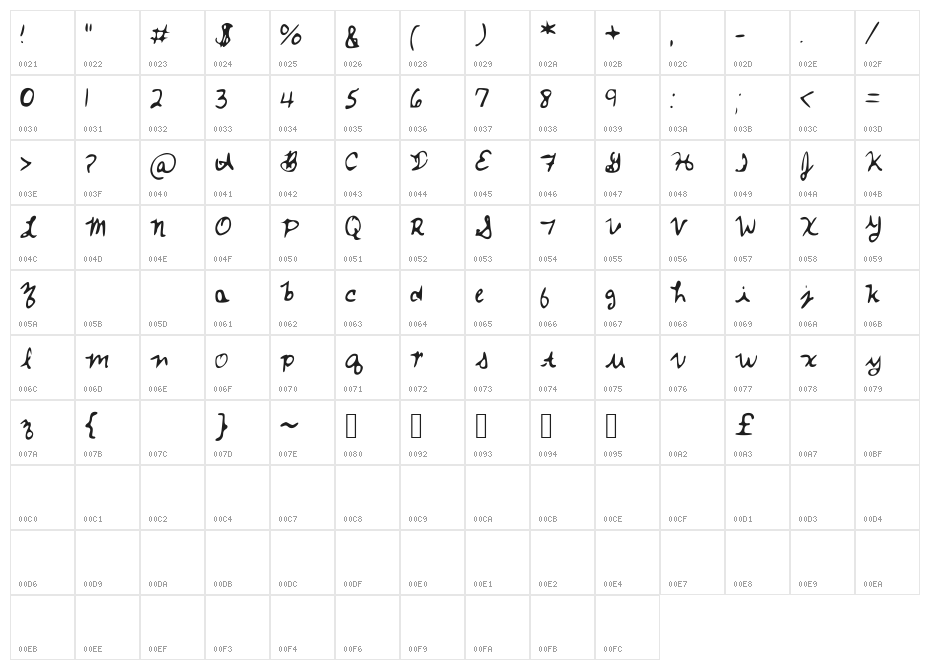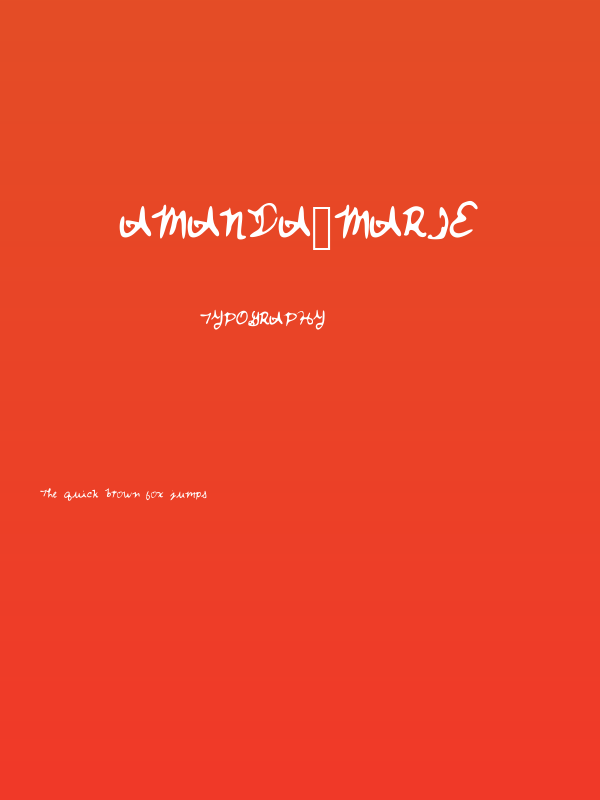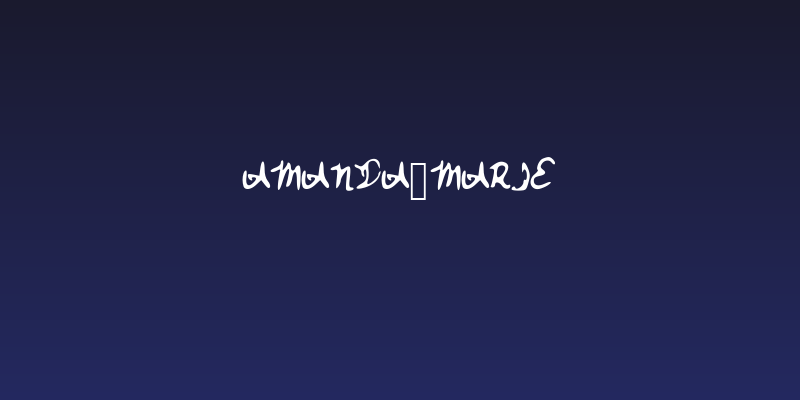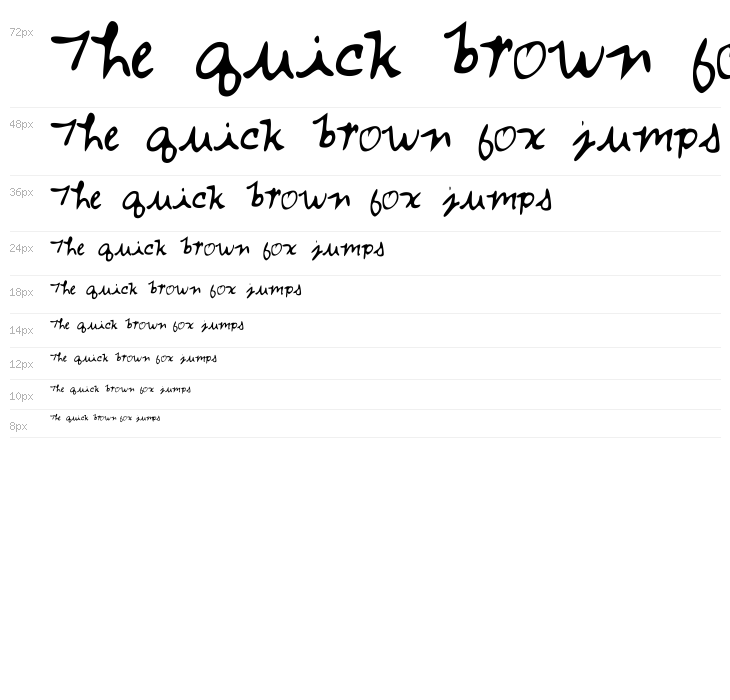
Amanda_Marie Font
Amanda Marie
| حالة الاستخدام | Logos, Posters, Invitations |
| مشاريع مقترحة | Ideal for creative projects such as invitations, greeting cards, artistic posters, and branding materials that require a unique and expressive touch. |
| المؤلف | Amanda Marie |